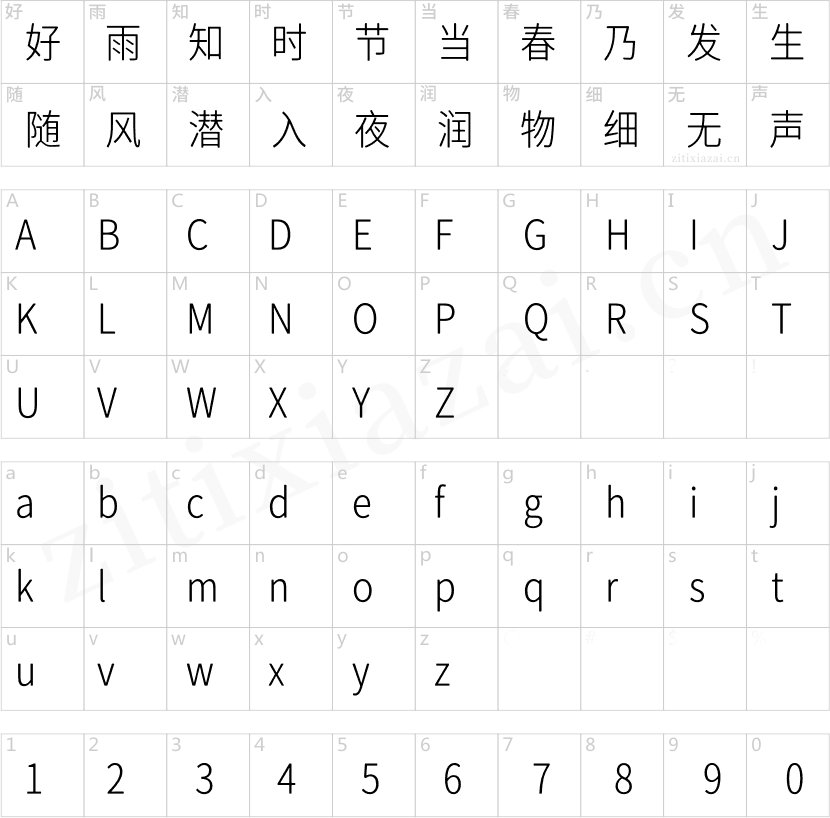
寒蝉云墨黑
寒蝉云墨黑,这款字体结构工整、笔画清晰,兼顾美观与易读性,适用于标题、正文、海报、包装、LOGO 等多种场景。字形优雅稳定,风格百搭耐看,适配日常排版与创意设计,让文字呈现更舒适、更具质感。寒蝉云墨黑一笔一画,皆是细节,以均衡的比例、流畅的线条打造舒适视觉体验,字形端正大气,风格简约现代。无论是商业设计、品牌宣传还是日常排版,都能轻松驾驭,让文字更有格调与力量。寒蝉云墨黑字体下载。
• 字体说明:基于思源黑体(SourceHanSansSC) 修改,添加圆角,更加温润的黑体。 排版细节优化,重构字重比例。寒蝉云墨黑是基于思源黑体进行调整的字型,采用SIL Open Font License 1.1授权发表。如甲方或公司需要出示授权文件,直接使用SIL Open Font License 1.1开源字体协议即可。